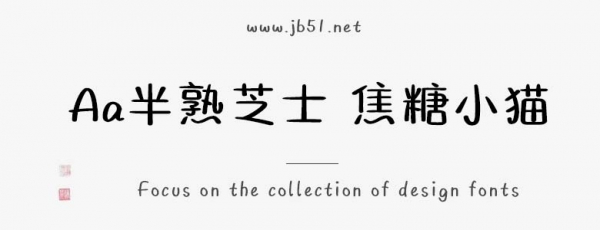
Aa半熟芝士 焦糖小貓字體筆觸略細(xì),書(shū)寫(xiě)流暢,略顯可愛(ài),具有很好的視覺(jué)感,適合應(yīng)用于藝術(shù)設(shè)計(jì)、平面宣傳設(shè)計(jì)、網(wǎng)頁(yè)設(shè)計(jì),書(shū)法字帖等領(lǐng)域。有需要的朋友快來(lái)本站下載使用吧。